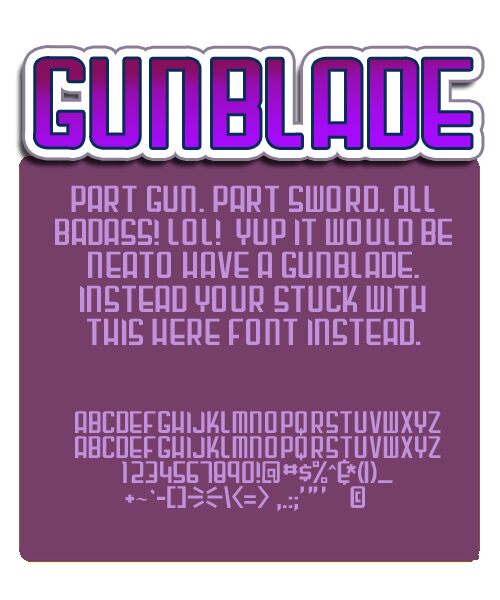
Gunblade to darmowy techniczny font typu display o surowym, "growym" charakterze. Wielkie litery zbudowano z ciężkich, prostokątnych pociągnięć i kwadratowych krzywizn, co nadaje im kompaktowy, pancerny wygląd – bardziej przypominający emblematy sci-fi czy napisy z automatów arcade niż neutralne, nowoczesne liternictwo.
Świetnie sprawdzi się w nagłówkach plakatów, logotypach gier, okładkach albumów, planszach tytułowych i brandingu sportowym, gdzie krótkie słowa wymagają zwartej, maszynowej sylwetki. Jako darmowy font, Gunblade doskonale nadaje się również do monogramów i napisów na okładkach, ponieważ litery łączą się w wyraziste, proste kształty, nie tracąc przy tym futurystycznego sznytu.